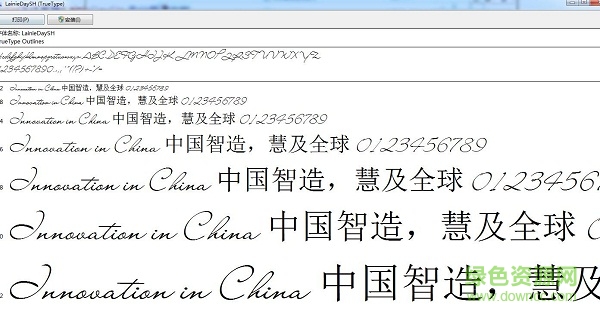
lainiedaysh.ttf常規(guī)
lainiedaysh.ttf常規(guī)字體是一款華麗的英文花體字體,線條飛揚灑脫,有一種舞動的美感,表現(xiàn)力非常強(qiáng),適合用在廣告設(shè)計、影視、包裝設(shè)計等領(lǐng)域,歡迎大家在綠色資源網(wǎng)免費下載!
lainiedaysh字體